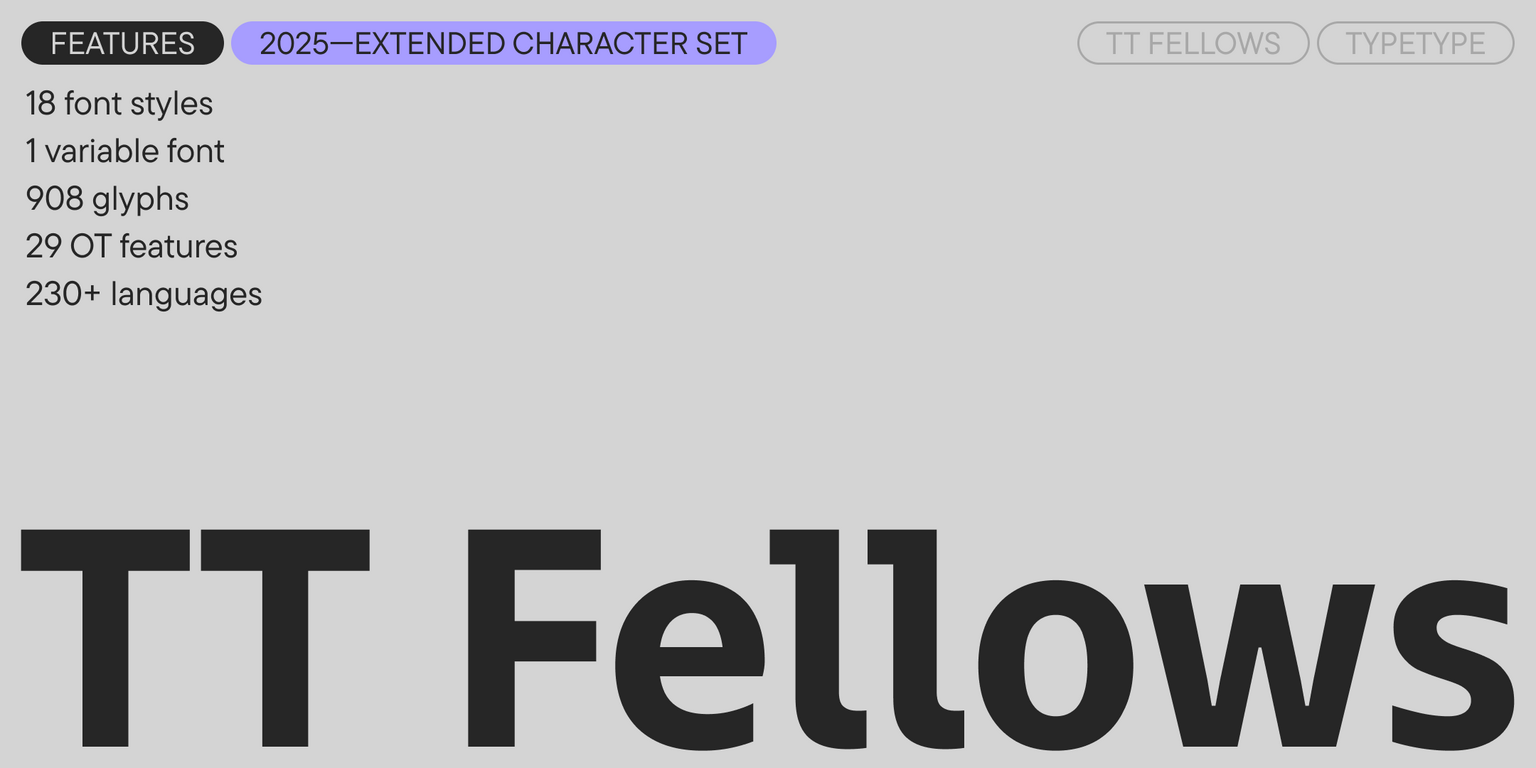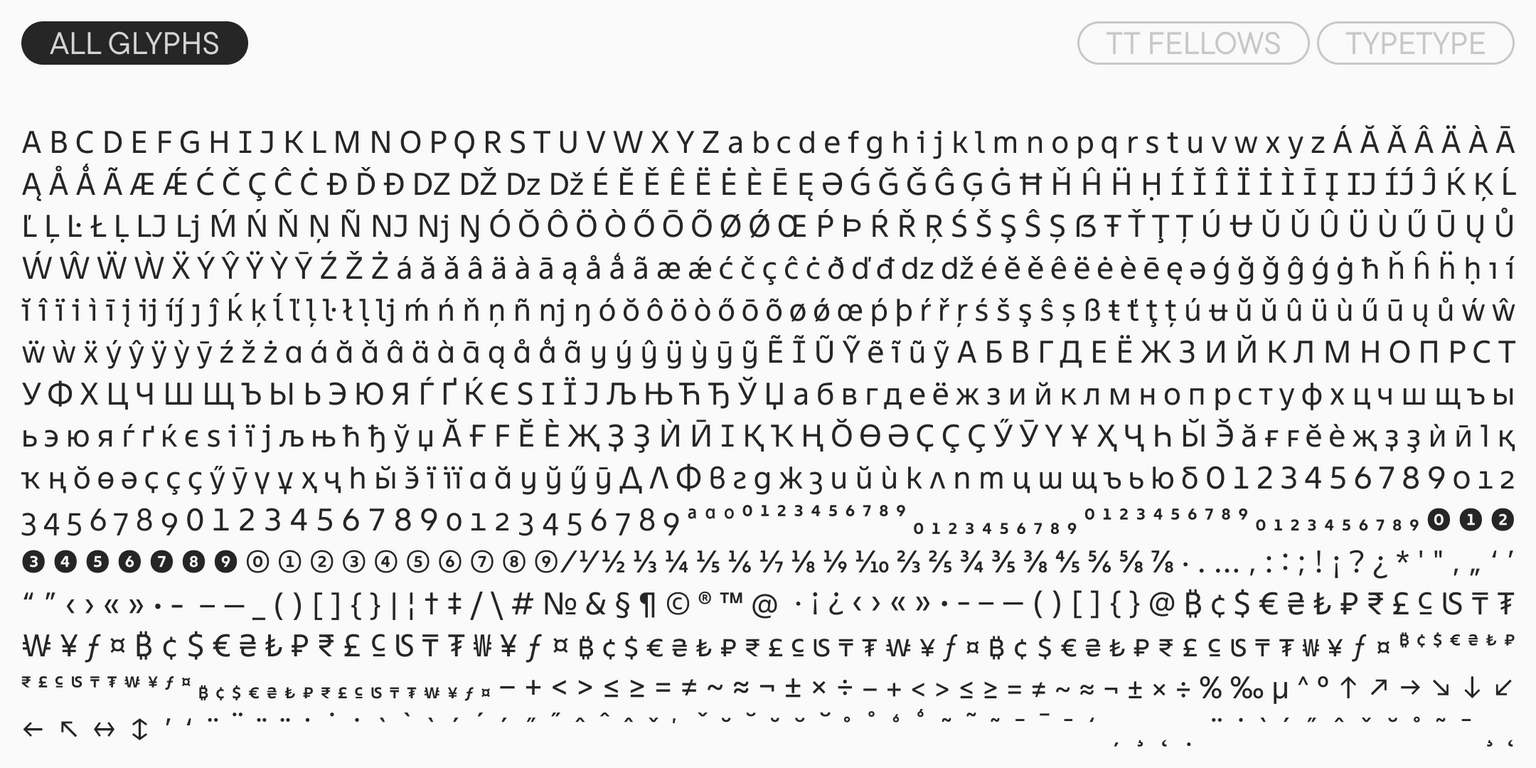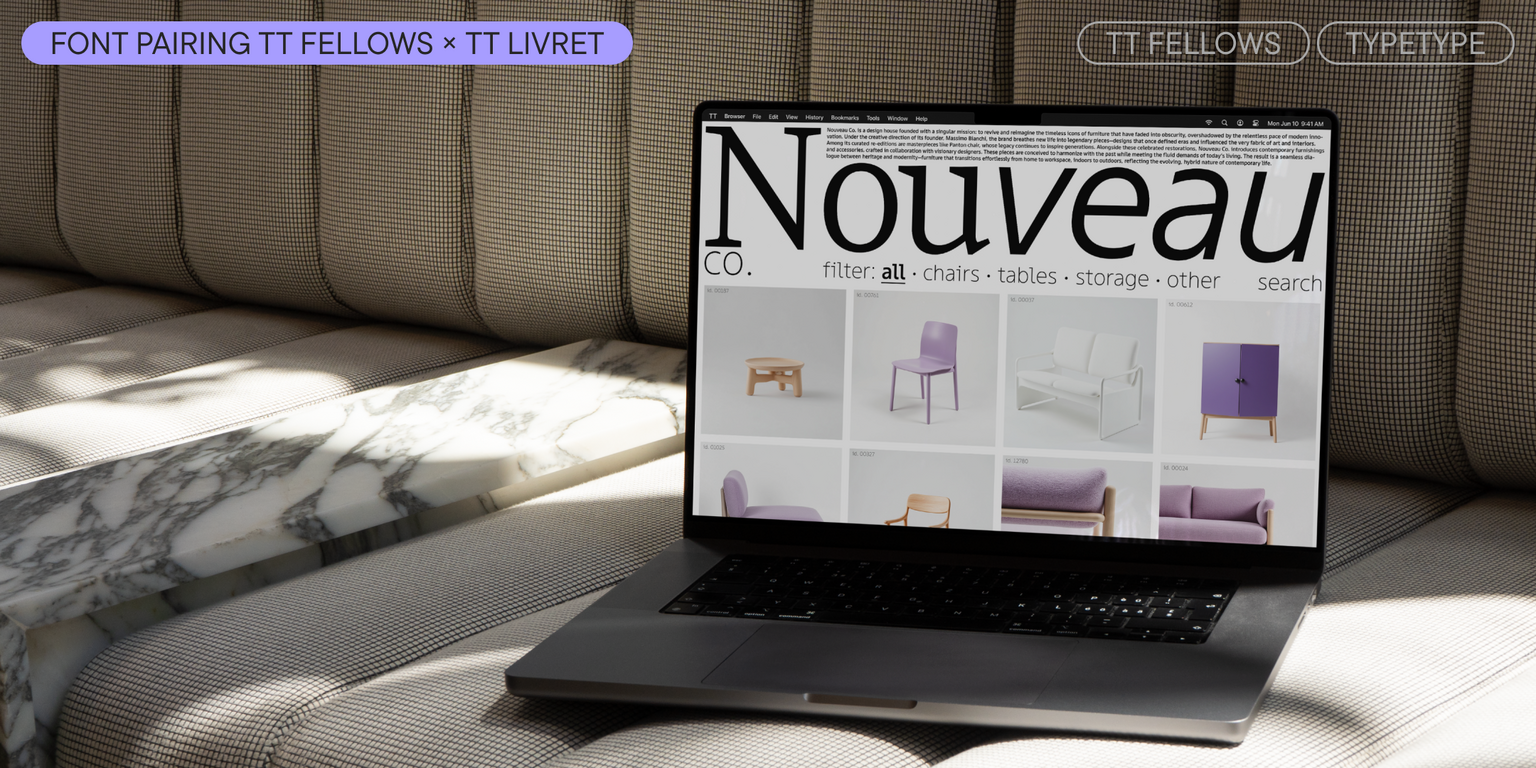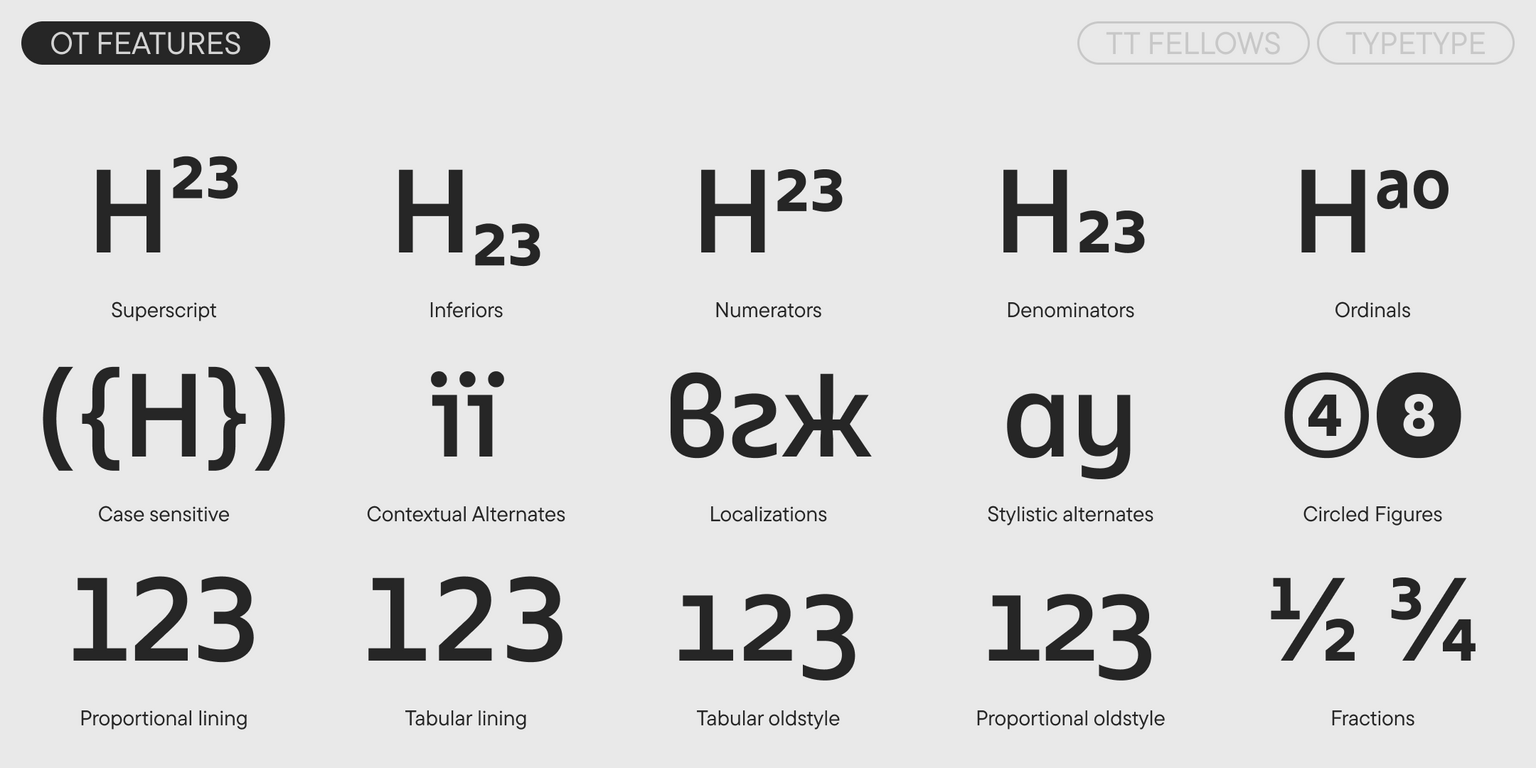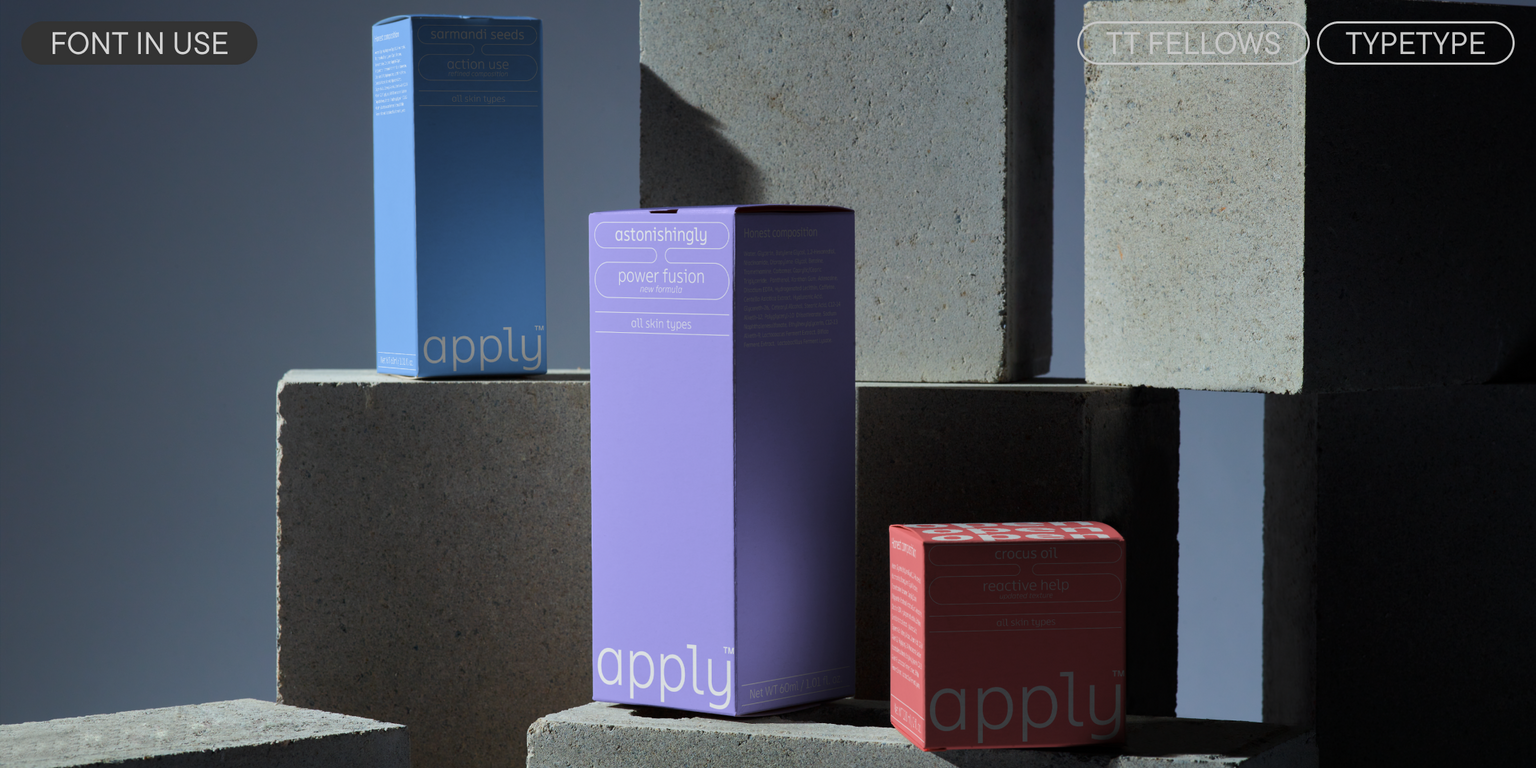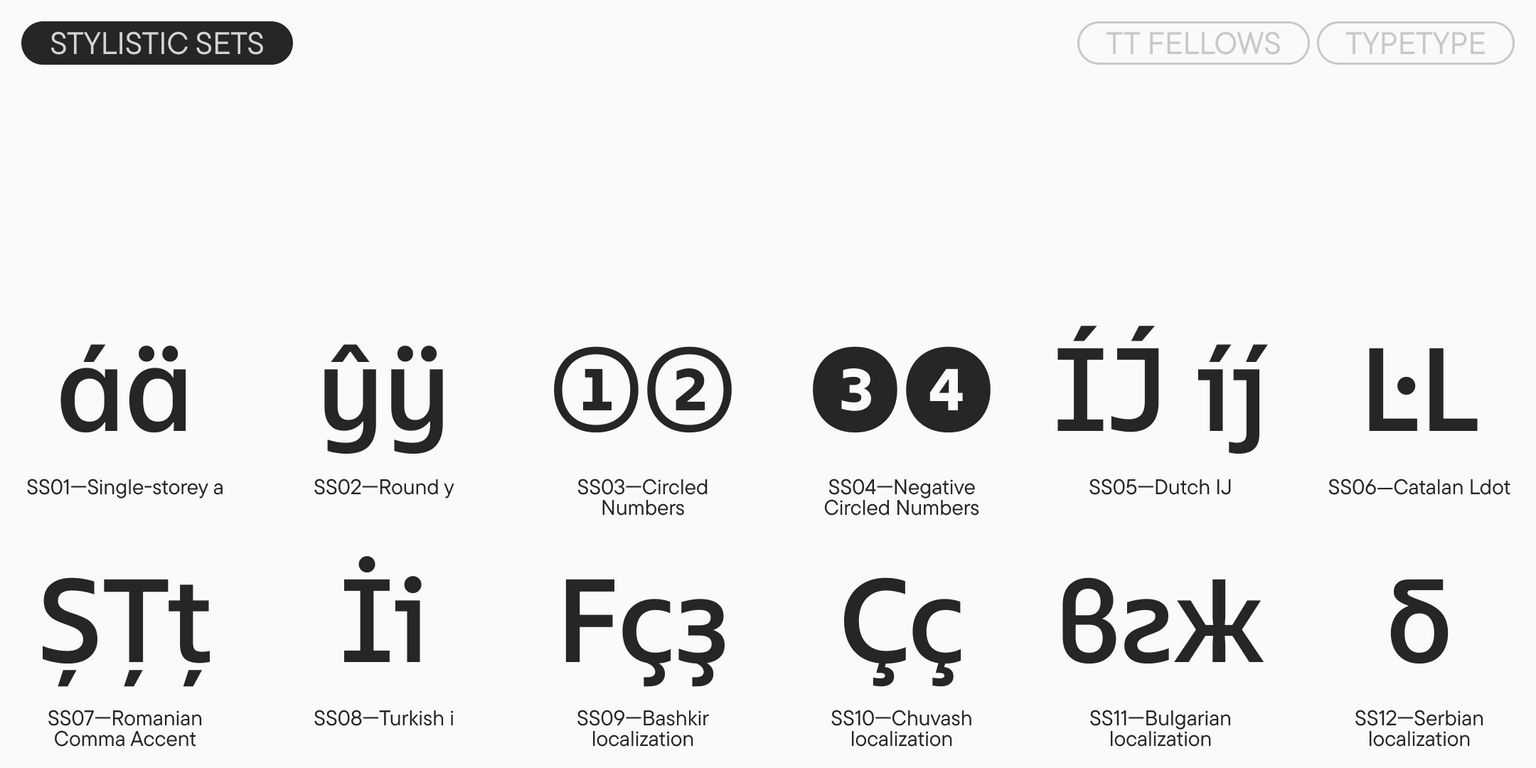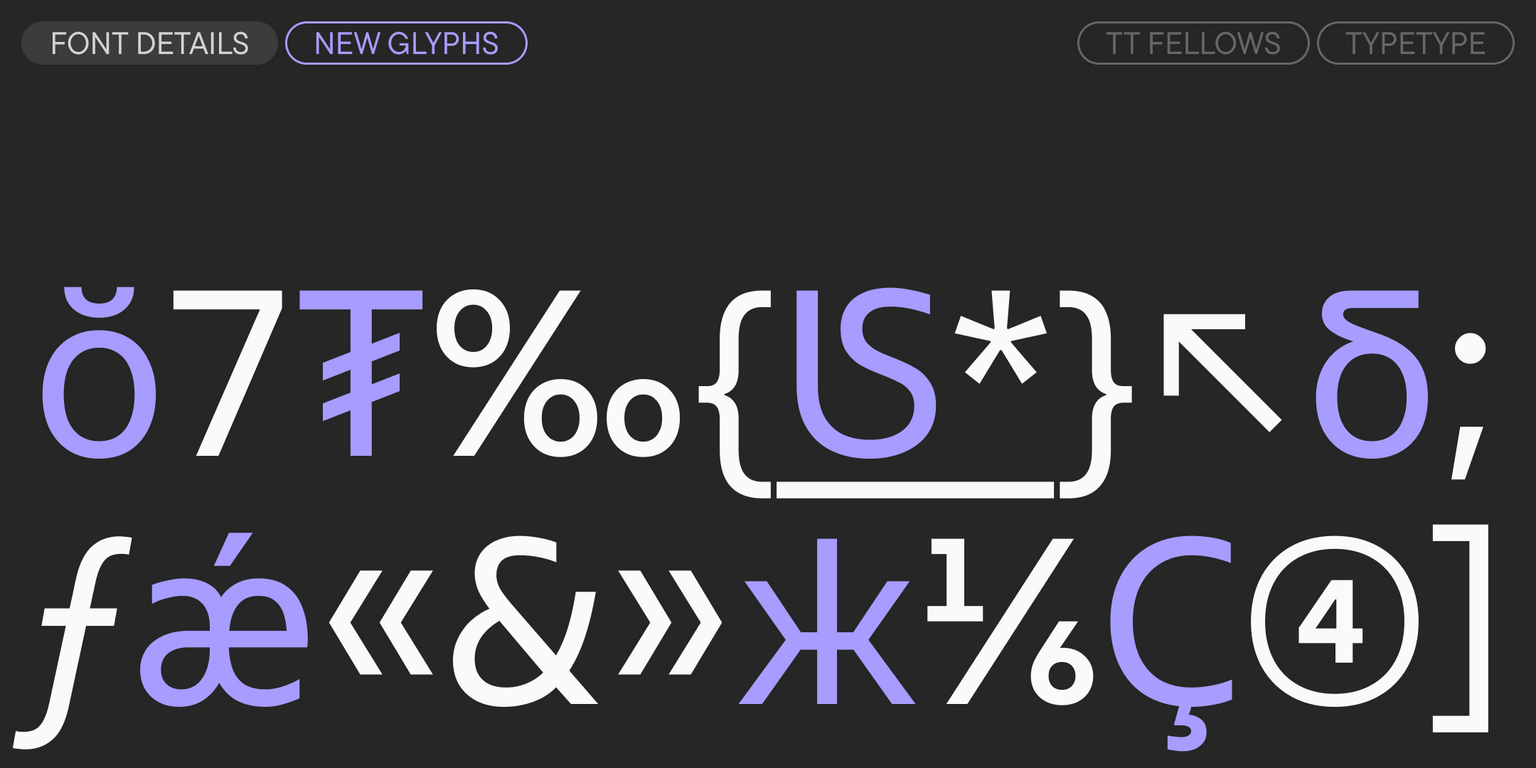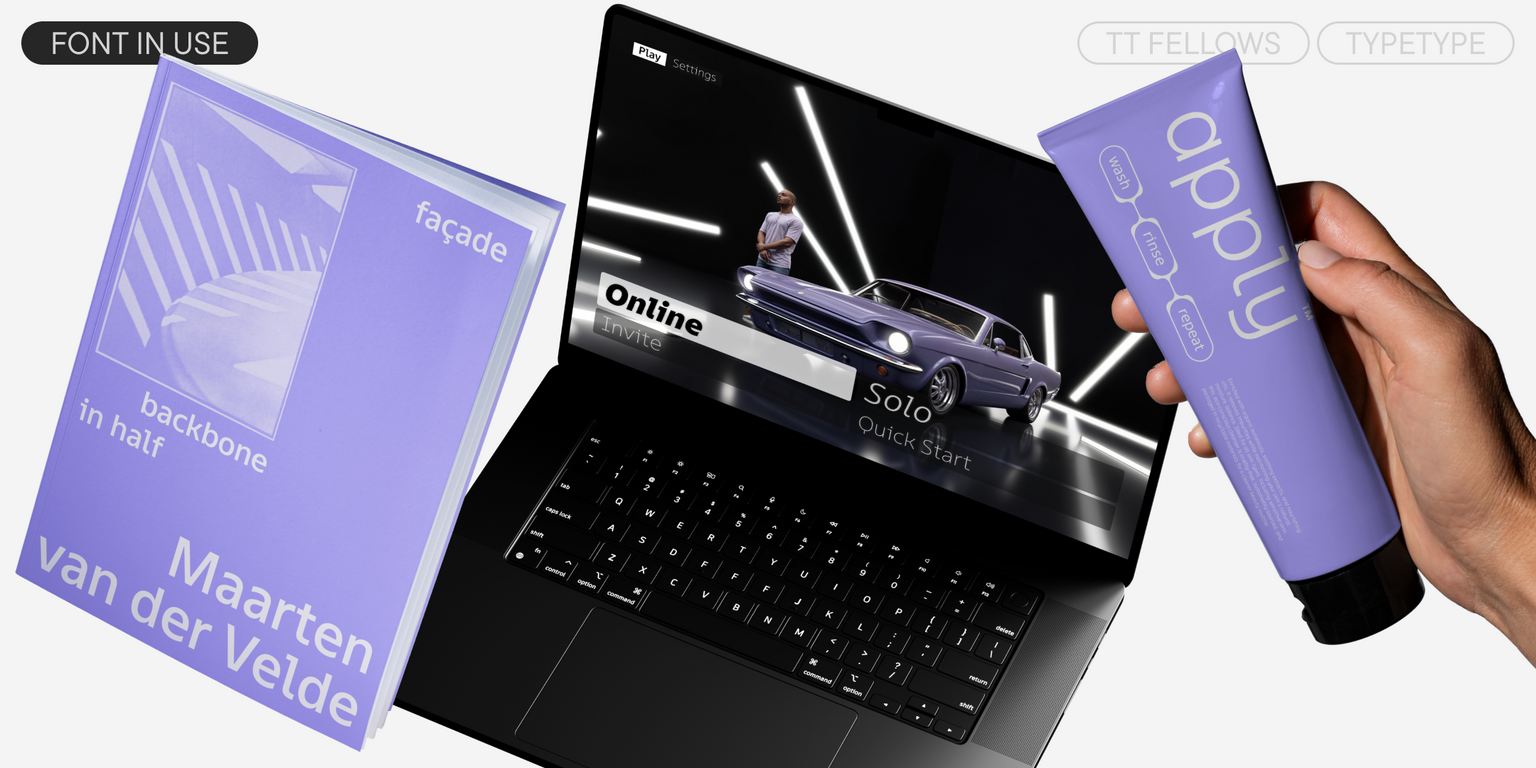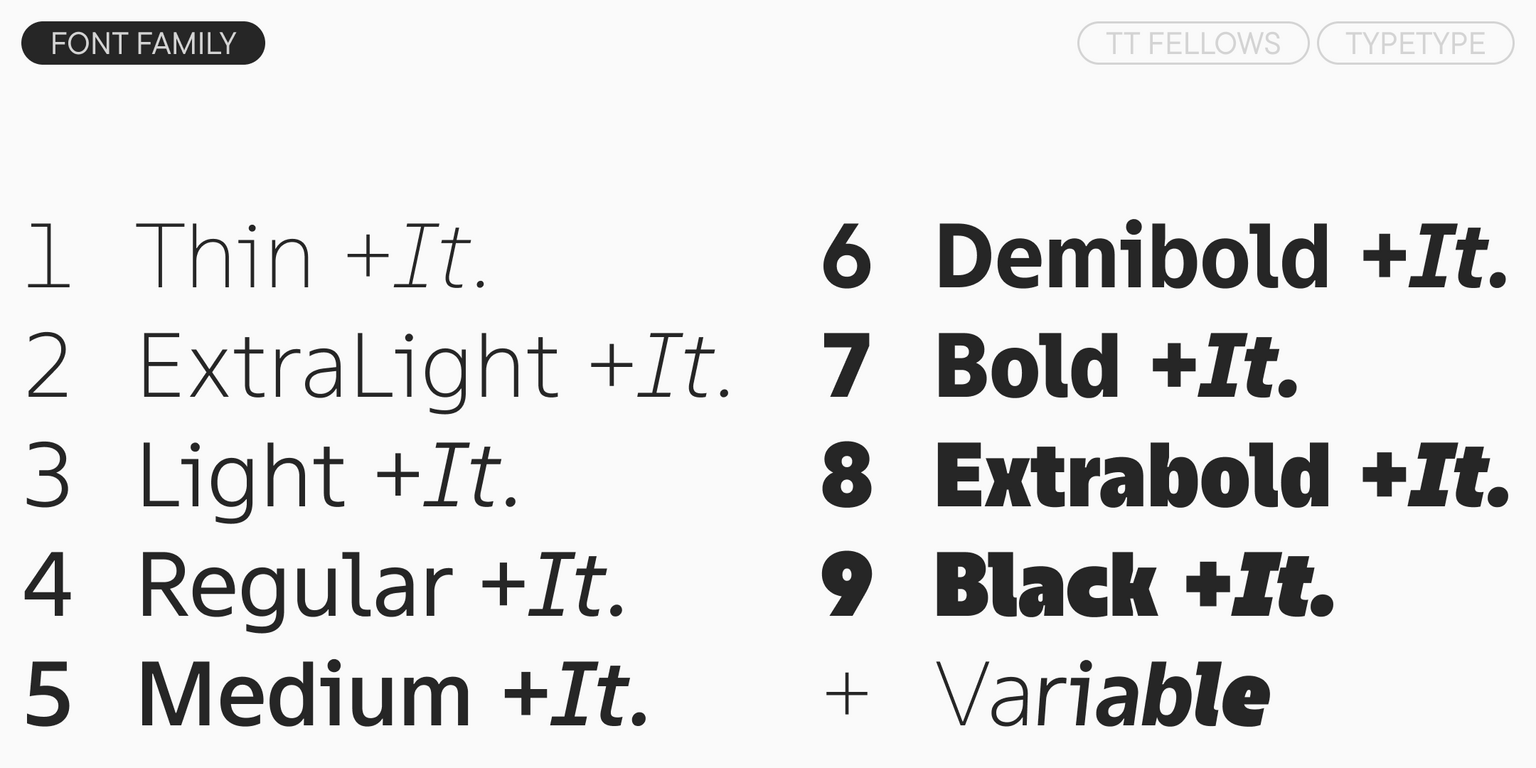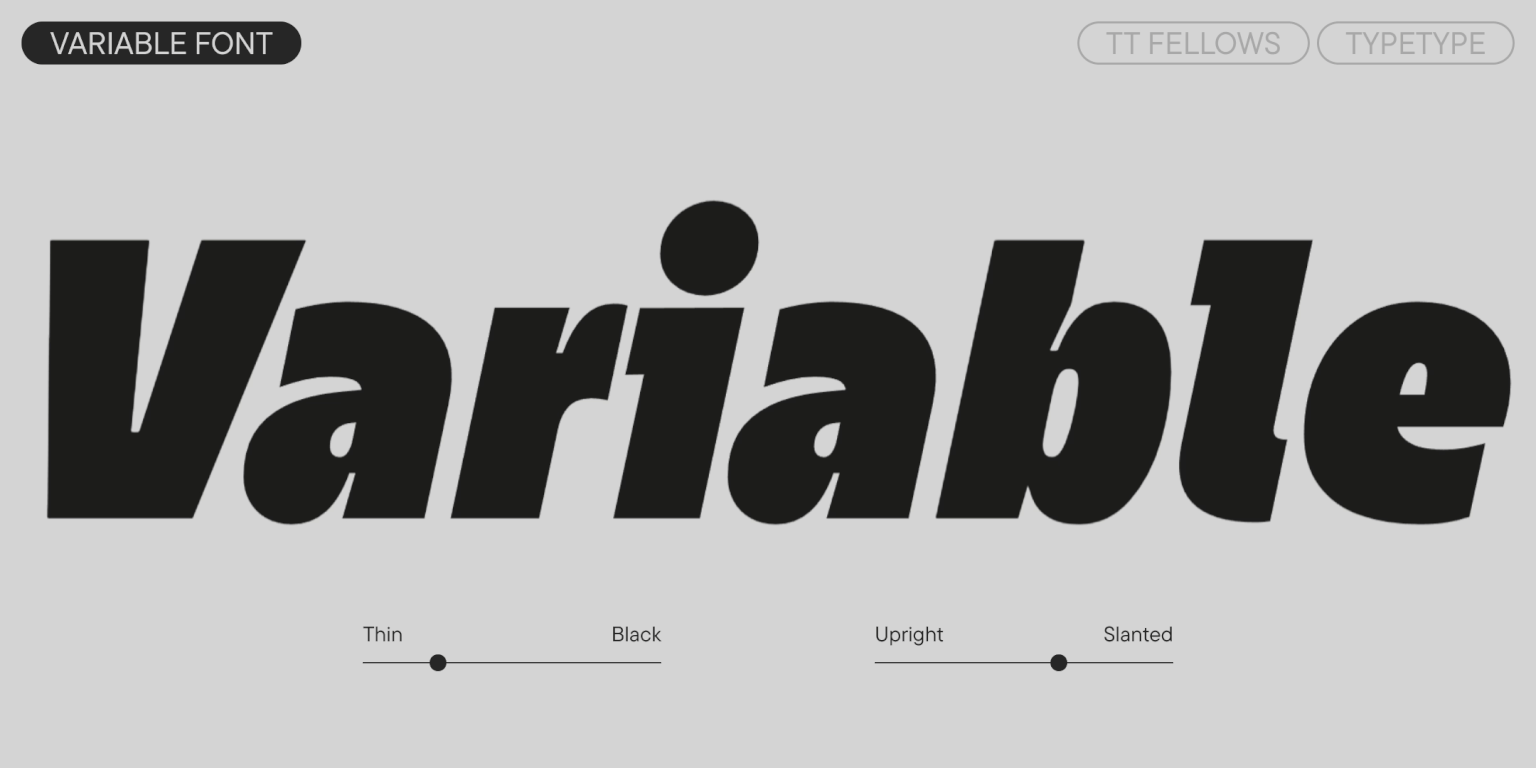
TT Fellows — ТТ Феллоус
Произносится «ТТ Феллоус». «Fellows» — производное слово от fellow, в переводе с английского «приятель». Буквы «TT» являются аббревиатурой названия компании.
TT Fellows — универсальный гуманистический гротеск с изменчивым характером. Это униширинный шрифт: вёрстка в макете не пострадает при изменении начертаний.
Кстати, TT Fellows — униширинный шрифт
TT Fellows удобен в применении и отлично подойдёт для набора крупных массивов текста. Благодаря униширинности и универсальности шрифт идеален для использования на сайте или в периодических изданиях. Жирные начертания будут гармонично смотреться в заголовках или в качестве акцентов на печатной продукции или упаковке. TT Fellows — гуманистический гротеск с механистическими мотивами. Открытые формы, дружелюбно-нейтральный характер тонких весов и ещё более мягкий характер в жирных начертаниях — новая шрифтовая гарнитура отличается по характеру от классических гротесков TT Norms® Pro и TT Commons™ Pro, обладая при этом такой же функциональностью. Спокойные регулярные начертания шрифта отличаются от жирных, нарочито дисплейных и более выразительных.
TT Fellows состоит из 19 начертаний: 9 прямых, 9 наклонных и 1 вариативного шрифта, в состав каждого из которых входит более 900 глифов
Шрифт содержит 29 полезных OpenType фич
О гарнитуре TT Fellows
Встречайте усовершенствованный TT Fellows!
Обновили этот функциональный шрифт до версии 1.100: значительно расширили кассовый состав, дополнили стилистические альтернативы, добавили новые фичи и языки.
TT Fellows — гуманистический гротеск с открытыми формами и механистическими мотивами. Характер этого шрифта на первый взгляд спокойный и нейтральный, однако его настроение может меняться. В жирных весах он выглядит мягко и дружелюбно, а в тонких становится более сдержанным и лаконичным.
Немаловажно, что TT Fellows — униширинный шрифт, а значит вёрстка в макете не пострадает при изменении начертаний. Среди особенностей рисунка — равноширинные пропорции, открытые апертуры и немного сквадраченные овалы. Кроме того, в гарнитуру входит вариативное начертание, которое позволяет менять шрифт по осям жирности и наклона, подстраивая его под разные задачи.
При обновлении гарнитуры мы дорисовали расширенную кириллицу и дополнили латиницу, расширили основной набор валют, в том числе добавили валюты для нумераторов / денумераторов, минускульных и минускульных табулярных цифр и дроби. Также дополнили стилистические сеты, добавили новые полезные OpenType фичи и языки.
TT Fellows удобен в применении и отлично подойдёт для набора крупных массивов текста. Благодаря униширинности и универсальности этот шрифт идеален для использования на сайтах, в мобильных приложениях или в печатных изданиях. А жирные начертания будут гармонично смотреться в заголовках, помогут создать яркий акцент в брендинге или на упаковке.
В TT Fellows версии 1.100 входит:
• 19 начертаний: 9 прямых, 9 наклонных и 1 вариативный шрифт;
• 908 знаков в каждом начертании;
• 29 OpenType фич;
• Поддержка более 230 языков.
TT Fellows — надёжный шрифтовой приятель, готовый прийти на помощь дизайнеру в любой ситуации!
ss01 | Single-Storey a
a
ss02 | Round y
y
ss03 | Circled Figures
1 2
ss04 | Negative Circled Figures
3 4
dlig | Discretionary ligatures
1/2
case | Case Sensitive Forms
({[H]})